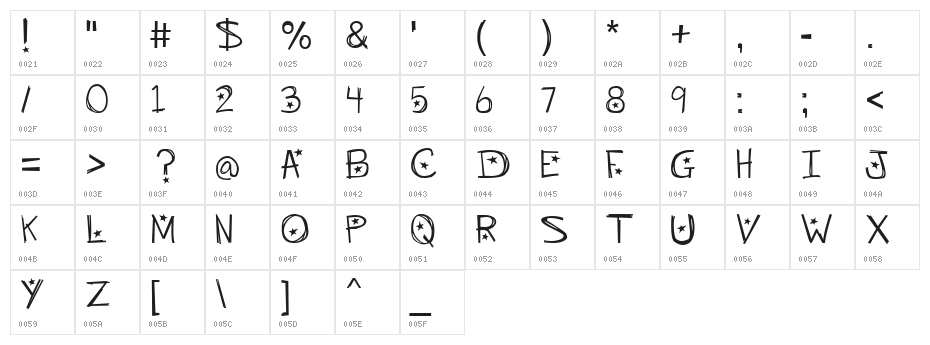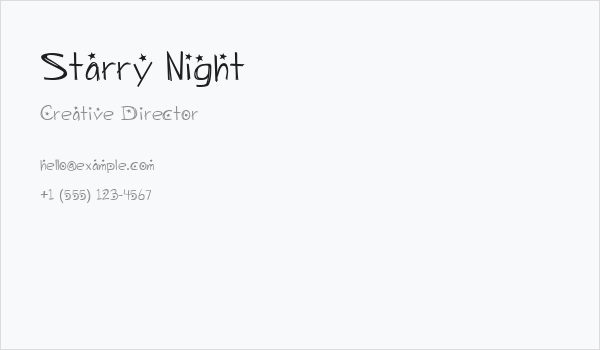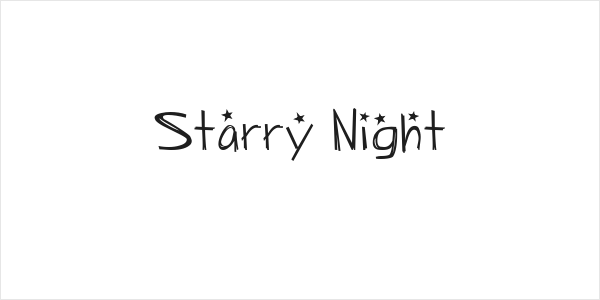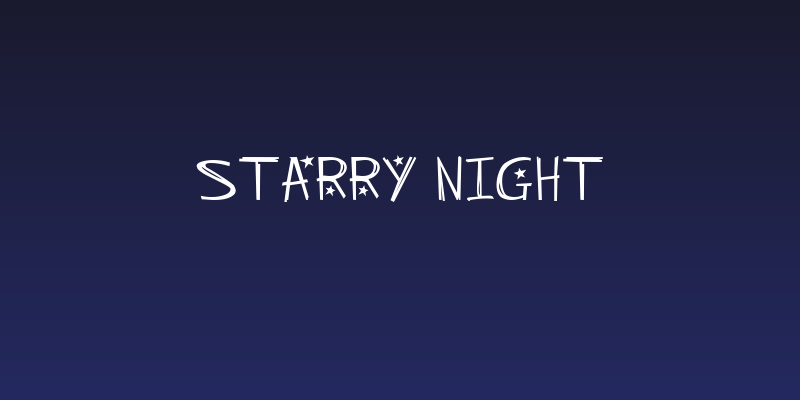
Starry Night Font
| Vorgeschlagene Projekte | Ideal for children's book covers, party invitations, fantasy-themed posters, or any project needing a whimsical touch. |